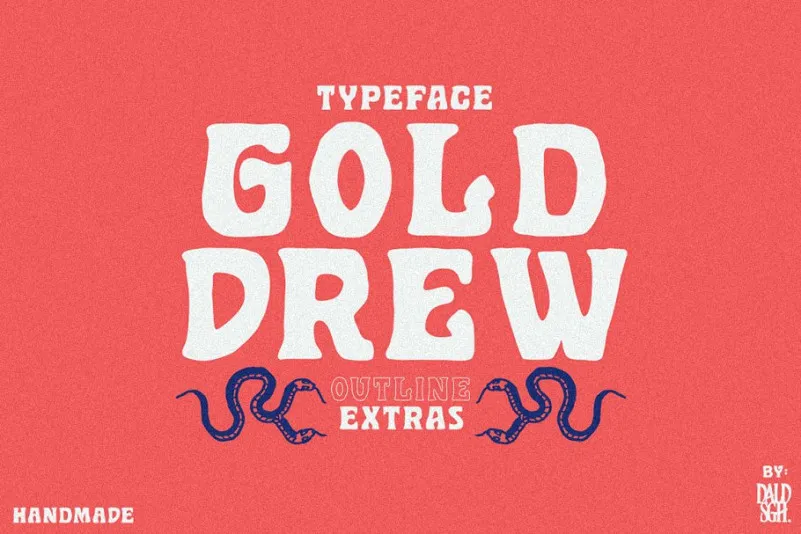
Golddrew Display Font – Download Grátis
Introduzimos a Golddrew Font! Ela é criada e compartilhada por DaldSgh. Golddrew é uma fonte escrita à mão com caracteres alternativos, perfeitamente adequados para um grande número de projetos gráficos como revistas, embalagens, marcas, cabeçalhos de sites, panfletos, assinaturas de carta, entre outros projetos criativos. A Golddrew não apenas se destaca por sua aparência elegante e fluida, mas também pela flexibilidade em adaptar-se a diversos contextos design. Seja para o interior de um site que exige uma aparência sofisticada ou para criar identidade visual impactantes em materiais promocionais, esta fonte oferece inúmeras possibilidades criativas. Experimente Golddrew e transforme seus projetos digitais em verdadeiros estandartes da moda moderna!